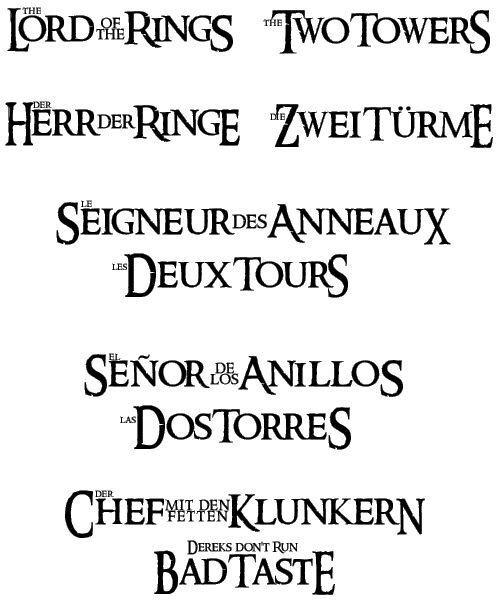
Ringbearer Medium
Ringbearer autorstwa Pete’a Klassena to darmowy, fantasy’owy krój szeryfowy typu display, utrzymany w średniowiecznym, baśniowym klimacie. Wielkie litery łączą wysokie, dostojne proporcje z ostrymi, klinowatymi zakończeniami i kilkoma surowymi, niemal ciosanymi krawędziami, dzięki czemu litery sprawiają wrażenie ceremonialnych, a nie wygładzonych.
Doskonale pasuje do okładek książek, filmowych napisów tytułowych, logotypów gier, plakatów eventowych czy otwarć rozdziałów, gdzie darmowa czcionka ma sugerować mity, wyprawy i dawne królestwa bez nadmiernego zdobnictwa. Wykorzystaj ją, gdy chcesz, aby krótkie nagłówki, monogramy czy znaki graficzne miały klimat w stylu Tolkiena – te litery same w sobie niosą ten wyryty, legendarny ton.